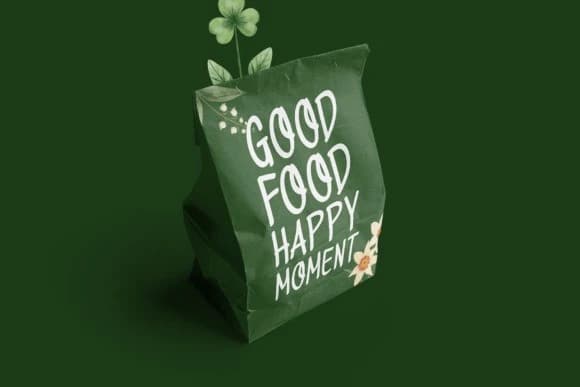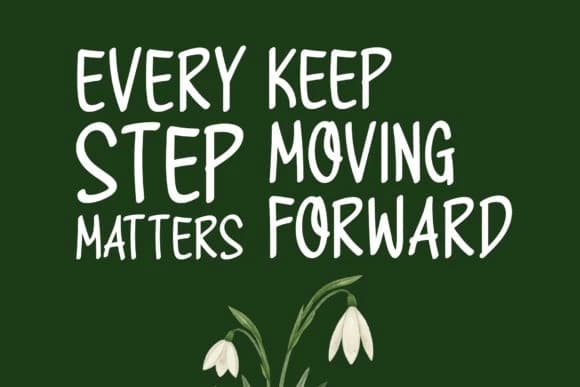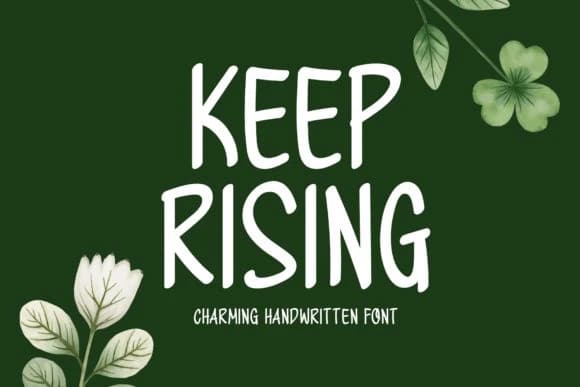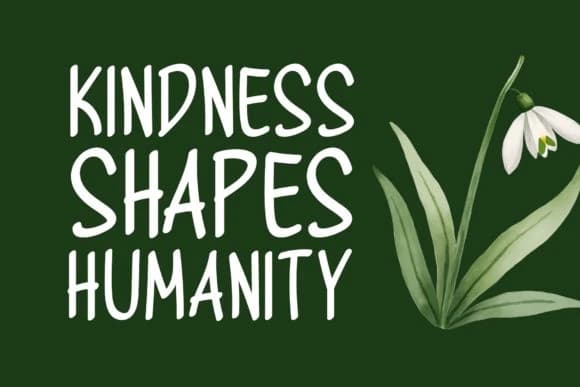
Keep Rising Font, uzun, ifadeli çizgilere sahip, akıcı bir el yazısı gösteri yazı tipidir ve her harfe doğal bir akış kazandırır. Rahat ve yükseltici tarzı, ilham veren alıntılar ve markalaşma materyalleri için mükemmel bir seçimdir.
Keep Rising Font, uzun ve ifadeli çizgilere sahip, her harfe doğal bir akış veren akıcı bir el yazısı gösterim fontudur. Rahat ve ilham verici tarzı, ilham veren alıntılar ve marka materyalleri için mükemmel bir seçenek yapar.